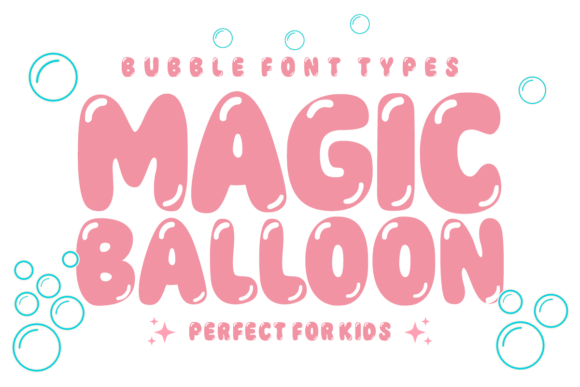
Magic Balloon
Magic Balloon – A Fonte que Transforma Criatividade Infantil em Arte
Se você procura uma tipografia que combine fofura, modernidade e versatilidade para projetos infantis, a Magic Balloon é a escolha perfeita. Esta fonte de balões de algodão traz um estilo gordo e moderno, composta exclusivamente por letras maiúsculas que se destacam em qualquer aplicação.
Por que a Magic Balloon é a Melhor Opção para Designers de Produtos Infantis?
- Design único e reconhecível: Cada caractere possui traços arredondados e detalhes encantadores que facilitam a identificação instantânea.
- Versatilidade de uso: Ideal para roupas sublimadas, canecas, sacolas, animações, títulos de quadrinhos, livros de colorir e demais itens infantis.
- Alta legibilidade: Mesmo em tamanhos pequenos, a fonte mantém clareza, garantindo que mensagens para crianças sejam sempre compreendidas.
Como a Magic Balloon Pode Elevar Seu Projeto
Imagine uma linha de camisetas com frases como DIVIRTA-SE ou SONHE GRANDE usando a Magic Balloon – o efeito “balão” cria uma sensação lúdica que atrai imediatamente a atenção das crianças e dos pais. Em livros de colorir, as letras se transformam em personagens que convidam ao desenho, enquanto em animações a tipografia adiciona dinamismo e charme.
Dicas de Uso para Maximizar o Impacto
- Combine a Magic Balloon com cores pastel ou neon para reforçar o aspecto divertido.
- Use sombras suaves ou contornos brancos para melhorar a legibilidade em fundos escuros.
- Experimente efeitos de “sublimação” para criar texturas que lembram balões reais.
- Integre ícones de brinquedos, estrelas ou corações ao redor das letras para composições ainda mais atrativas.
Conclusão – A Fonte que Faz a Imaginação Voar
A Magic Balloon não é apenas mais uma fonte; é um convite à criatividade sem limites. Seja para crafts escolares, produtos de print‑on‑demand ou projetos digitais, ela garante que cada palavra pareça um balão pronto para estourar de alegria.